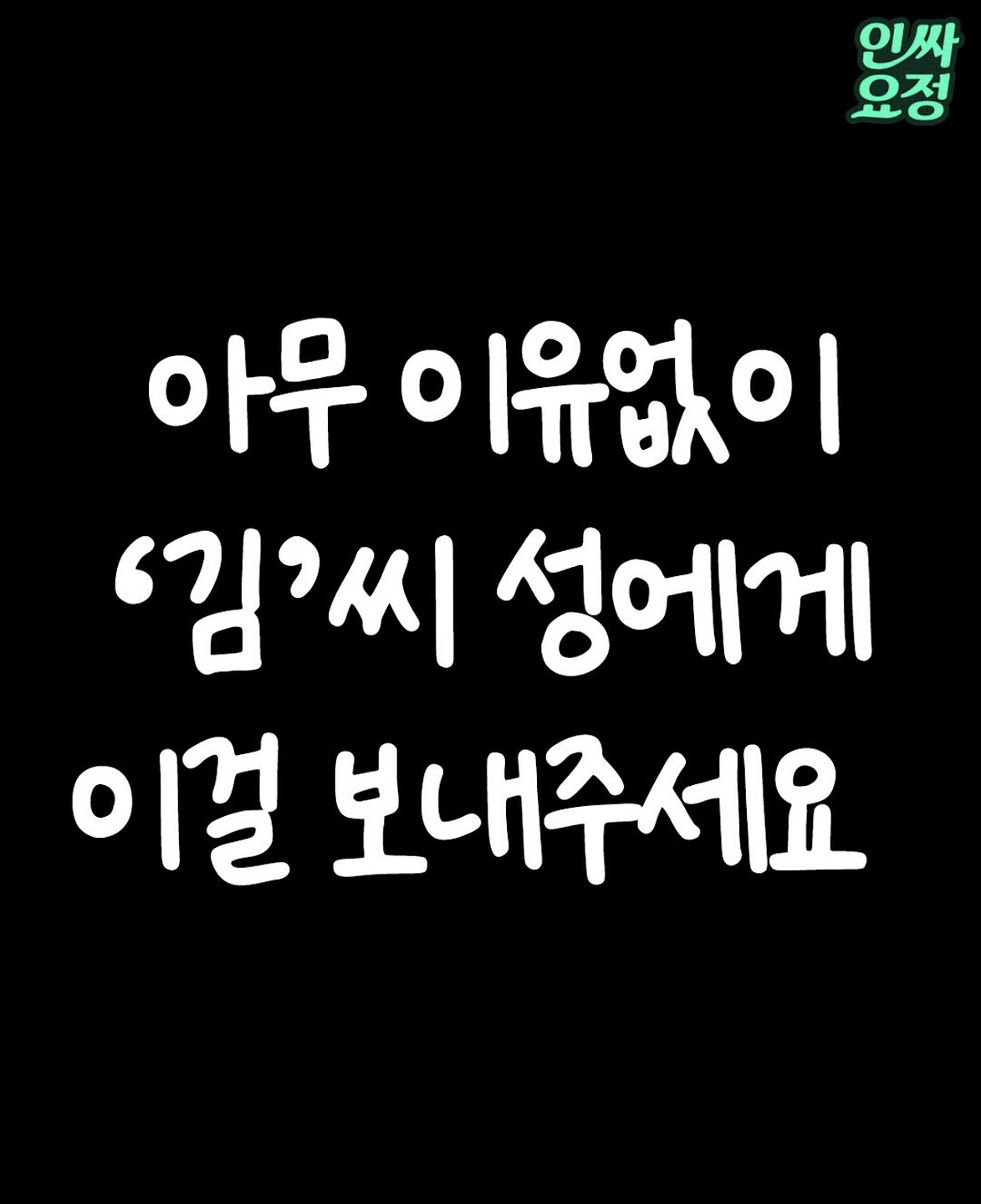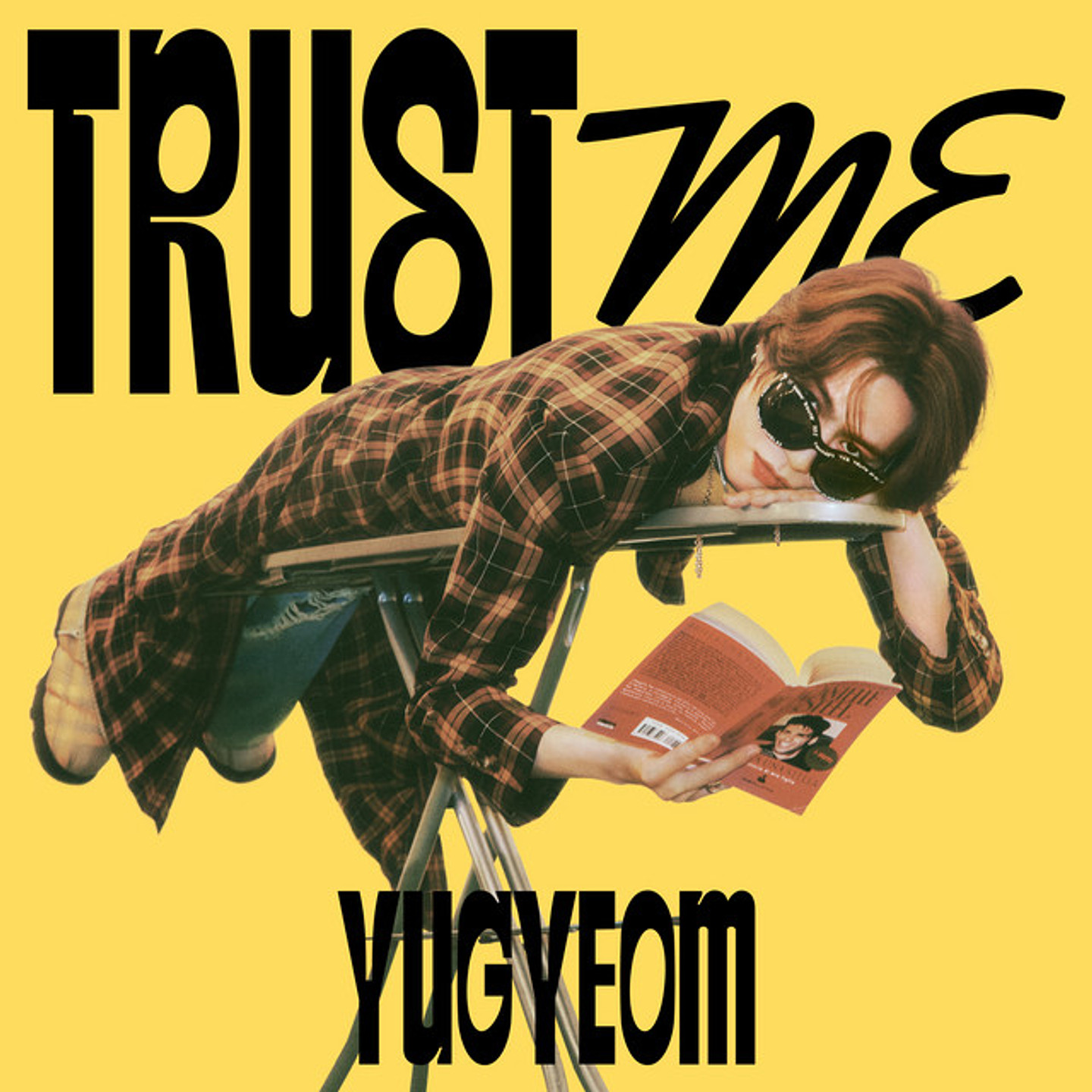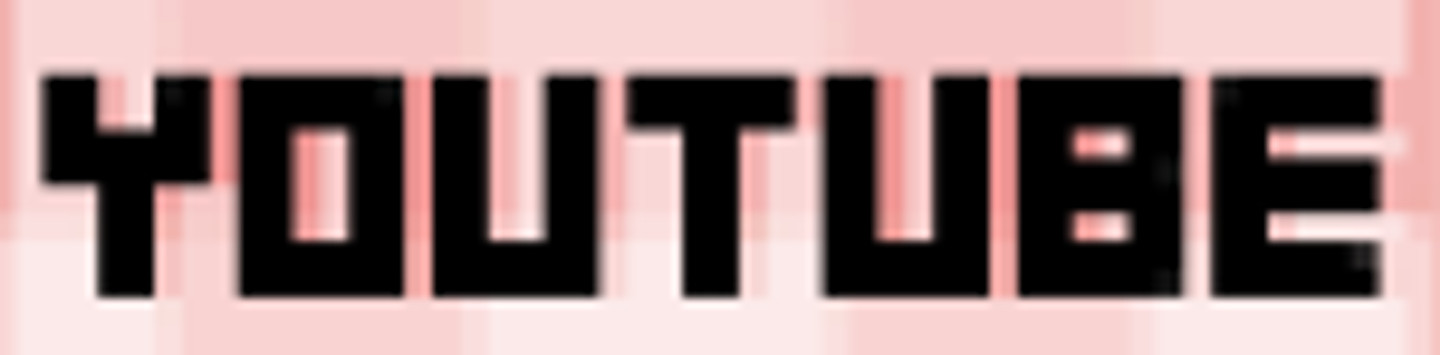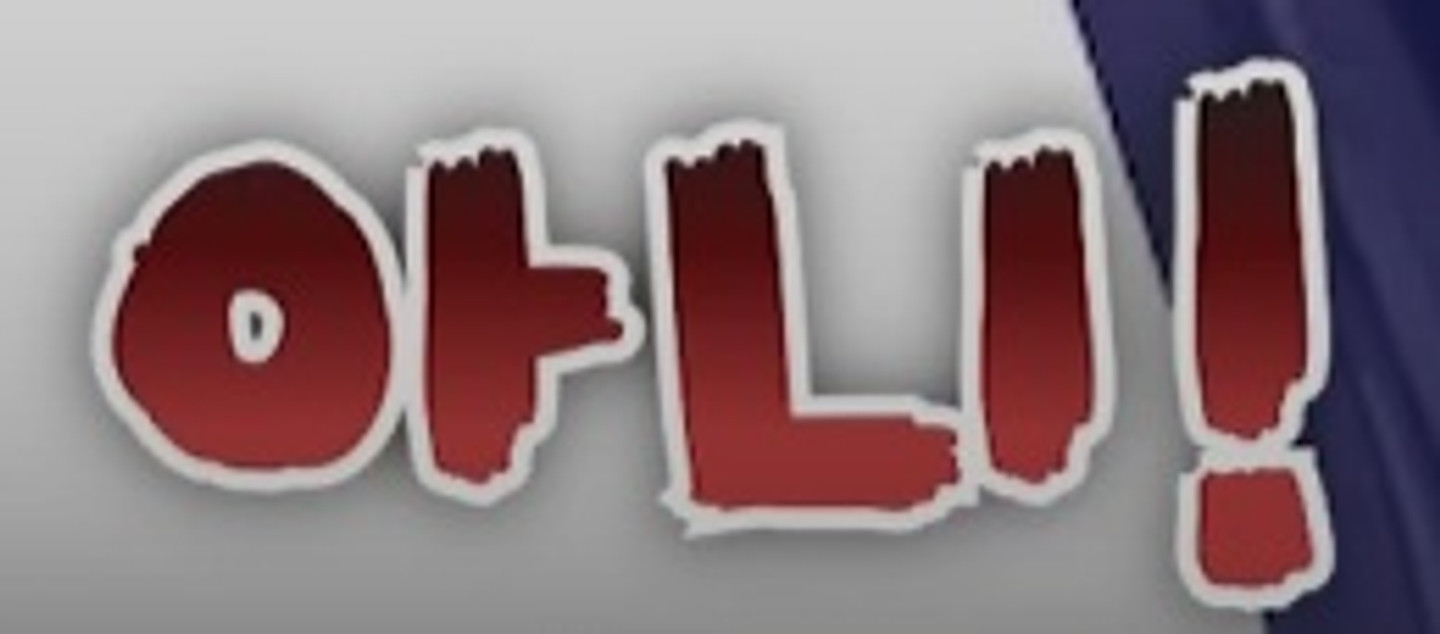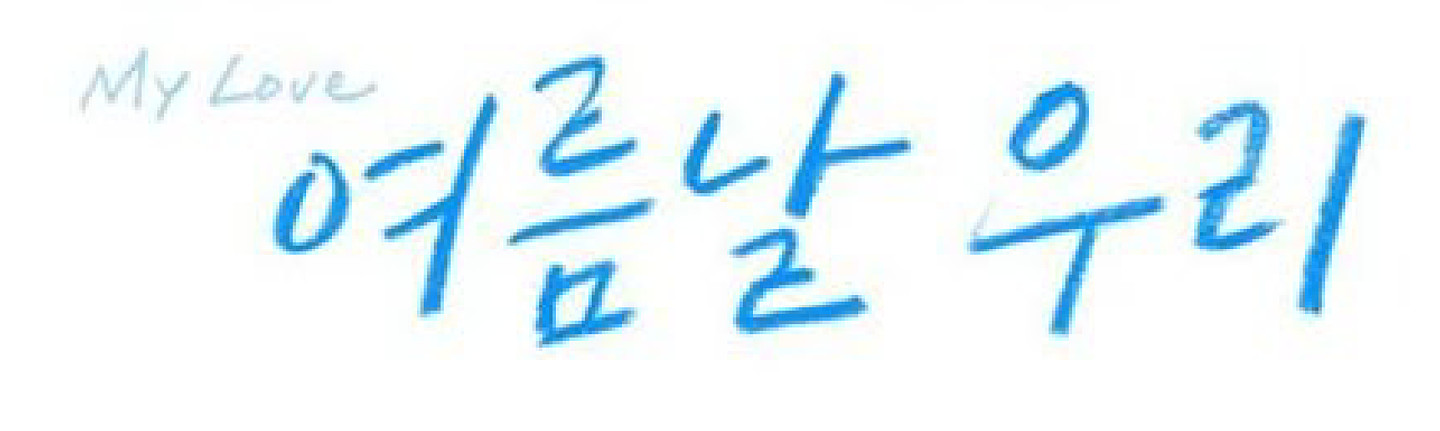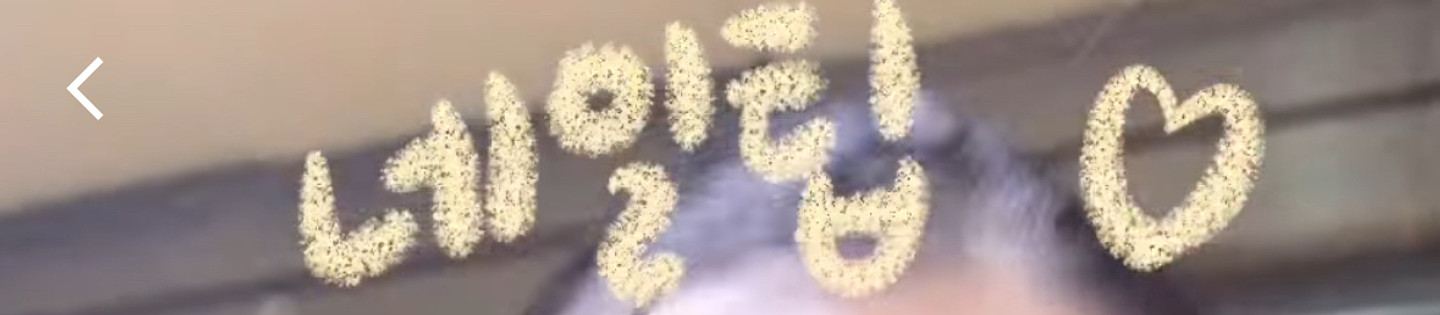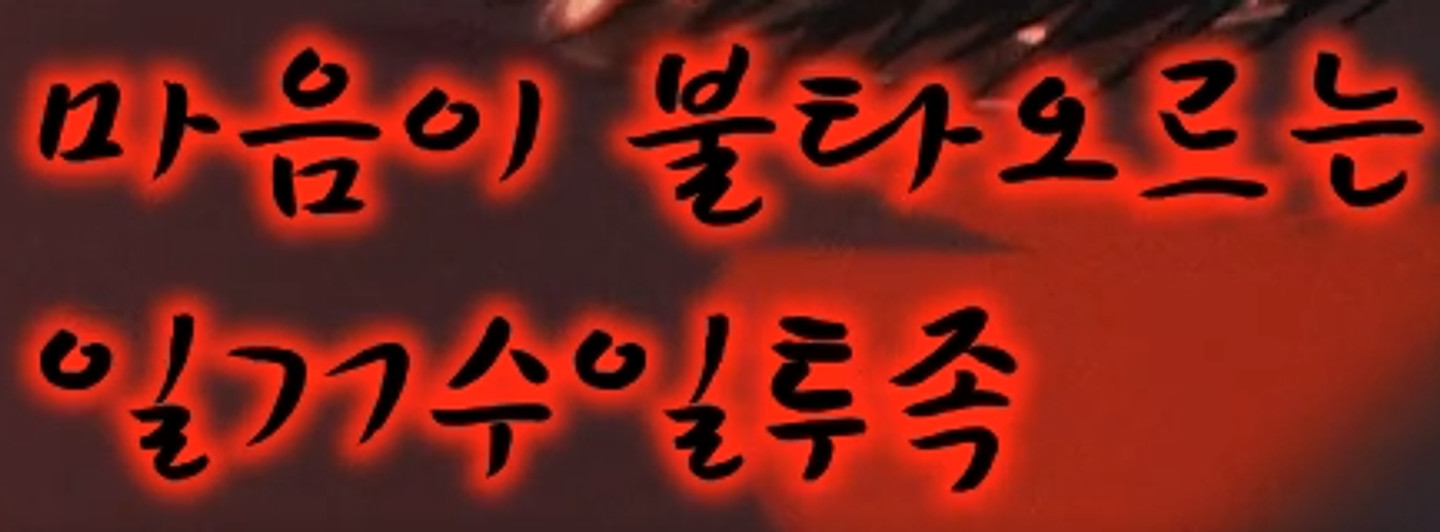
폰트뭘까요
옛날에 카톡에 있었던 폰트인데 이거 뭐에요ㅠㅠㅠㅠ 지피티나 ai 다 틀리게 말하더라고요ㅠㅠ
무슨 폰트인지 아시는분 계실까요..?
유튜브 영상인데 이 유튜버 폰트가 너무 알고싳어요ㅠㅠㅠ도어ㅏ주새요ㅠㅠㅠ
꽃보다청춘 리미티드에 나온 이 폰트 뭘까요?
무슨 폰트 일까요 !! 알려주시면 감사하겠습니당 ㅎㅎ
이 폰트 뭔가요 ㅠㅠ제발 알러주세오
마크 폰트 뭔지 궁금합니다.
위 영상에 사용된 폰트가 뭘까요?
폴라리스 오피스로 시나리오 보다가 궁금해서요. 한양신명조라고 뜨긴 하는데 HY신명조가 저렇게 자간이 좁지는 않잖아요. 다른 폰트인가요? 아니면 자간 조절을 한 걸까요? 알려주시면 감사하겠습니다.
이 폰트좀 알려주세요!
나주경찰서 한글, 영문 글씨체 알수있을까요?
무슨 폰트인지 궁금합니다ㅠㅠ
이 글씨체가 궁금해요 제발 찾아주세요ㅠㅠ
이 글씨체를 너무 사용하고 싶은데 어떤건지 잘 모르겠어요 ㅠㅠ
찾아줘 뭔지
폰트이름알고싶어요
안녕하세요 사진 속 폰트 무슨 폰트인지 알 수 있을까요? 아시는 분 답변 부탁드립니다!
무슨폰트인가요..?
고딕체
격동고딕, 본고딕은 아닌거 같구.. 헛갈리네요. 무슨폰트일까요
안녕하세요! 무슨 폰트인지 알수있을까요?? 감사합니다 :D
무한도전 스타일 이 폰트 궁금해요!
이거 폰트 뭔가요??
무슨 폰트일까요????
무슨폰트일까요 ...
가짜 김효연에 나오는 이 폰트 뭔가요????
무슨 폰트 일까용
한라대학교 전용서체가 필요해요ㅜㅜ 비슷한거라도ㅜ
고수님들 폰트 좀 알려주세요
이 폰트 궁금합니다.
어디서 많이 본 폰튼데 저 ㅅ이 안뜨네요ㅜㅜ
폰트 알고싶어영
하트 들어가있는 폰트 궁금해요
특이한 폰트인데 폰트가 뭘까요? 궁금합니다!
안녕하세요! 나혼자 북촌 요거 어느 폰트 인지 알수 있을까요?
한글이랑 영문폰트요
이 폰트 이름이 뭘까요ㅜㅜ
이 폰트 뭔가요 ㅠ.ㅠ
저화질이라 조금 보기 힘들 거 같은데용... 꼭 찾고 싶어요
팅팅팅팅 유튜브인데 어떤 폰트인가요?
이 폰트 아시는 분 없을까요?ㅠ
폰트 뭔가요?
어떤 폰트인가요
폰트찾아쥬세요!!
폰트 알려주세요 ㅠㅠ
이거 무슨 폰트 인가요?? ㅠㅠ 진짜 제발요 ㅠㅠ 넘 궁금해요 ㅠㅠ
이거 무슨글씨체인가요 ㅠㅠ?